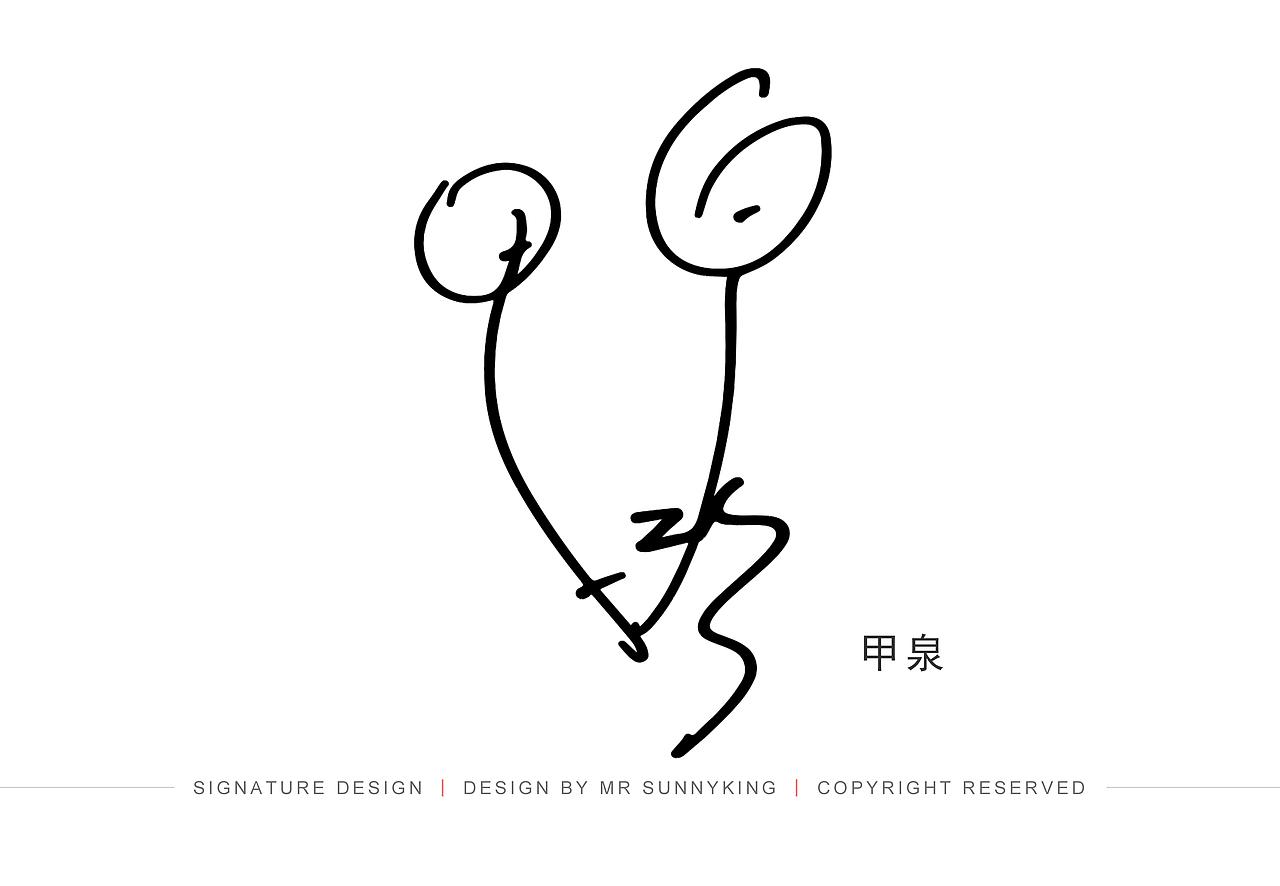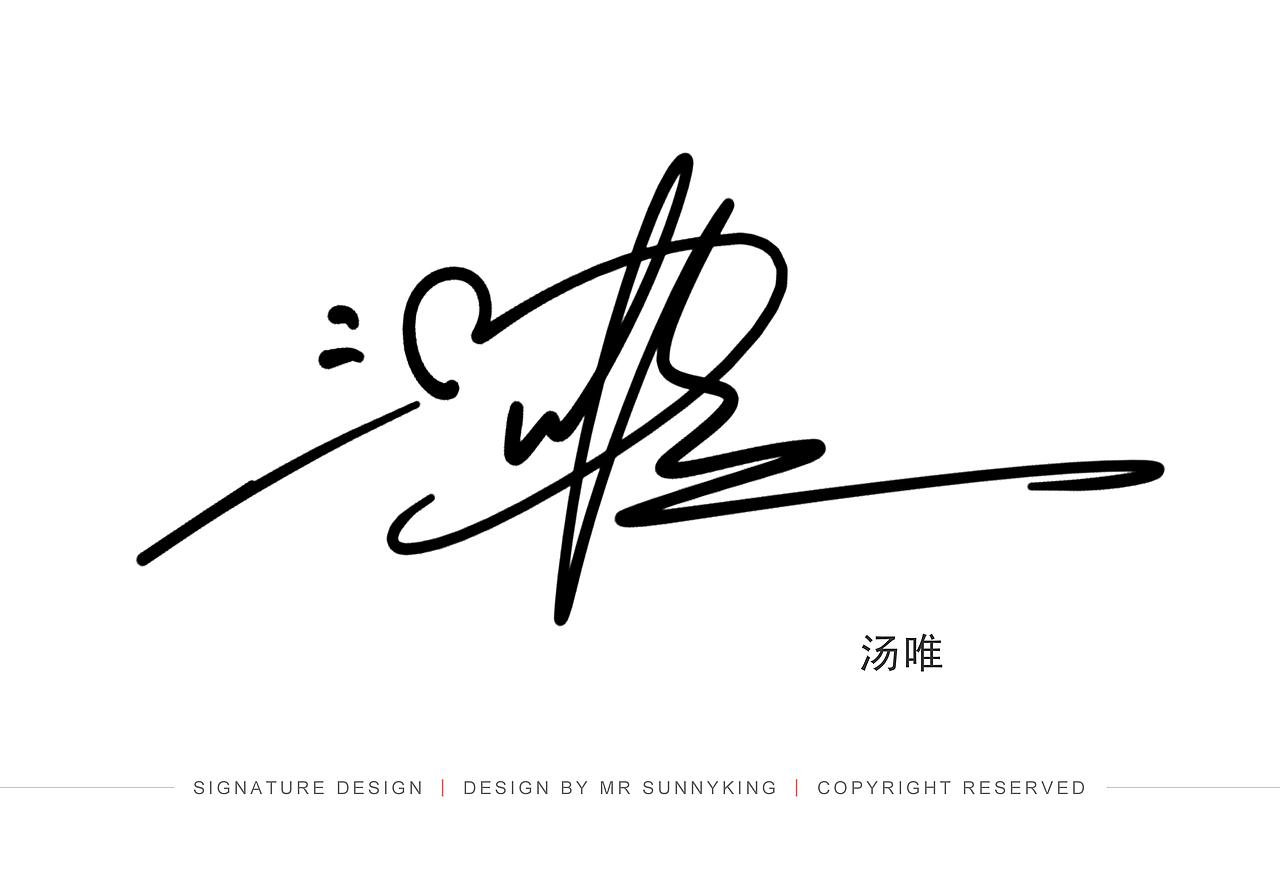
签名怎么写好看呢?这里有案例,学会可以DIY自己签名
为什么要设计我们的签名?签名设计与签名艺术的意义与社会价值?
签名设计的实际意义与重要性:
1.字如其人,签名是一个人的文化形象。漂亮的签名会给人们留下好印象;爱情,工作,事业上树立起自己良好的文化形象,带来更多成功的机会。
2.防伪性:签名通过专业签名设计师的设计和包装,别人很难模仿,独一无二;
3.提高效率:时间就是生命!一个几十笔画的签名通过专业设计后,几笔就能快速书写完成,潇洒流利,节省时间成本。
4.安全保障:每个人的签名皆具有法律效力!经过设计过的签名,只要是本人签写,即具有法律效力,同样受法律保护的!
5.提升魅力:好看的签名提升气质,彰显文化形象,体现内在修养。越成功的人士,往往更加注重细节!
6.增加自信:再也不怕在人多的场合签名了!漂亮的签名,赢得更多赞许的目光,让你自信满满!
7.身份的象征:各行各业,皆有起签名的特征和个性。好的签名是一个人的门面;通往成功之路,漂亮签名必将祝你一臂之力!
8.唯一性:签名伴随一生!一辈子可能就写这一个名字。如果自己的名字都写不好,都不认真去对待,如何去获取别人更多的信任?!每一个细节都决定着一个人的未来与成败!
9.文化传承:签名设计并非当今之物,早在唐宋时期就有画押(可理解为签名)。因此签名艺术是一种文化的传承,更是画押文化的创新!支持签名艺术设计,是一种时尚和文化自信的体现!
10.艺术性:签名本身就是一门独特的艺术,每个人的签名造型千姿百态,风格各有千秋,深究其中,方寸之间,趣味无穷。更有签名佳话代代相传。